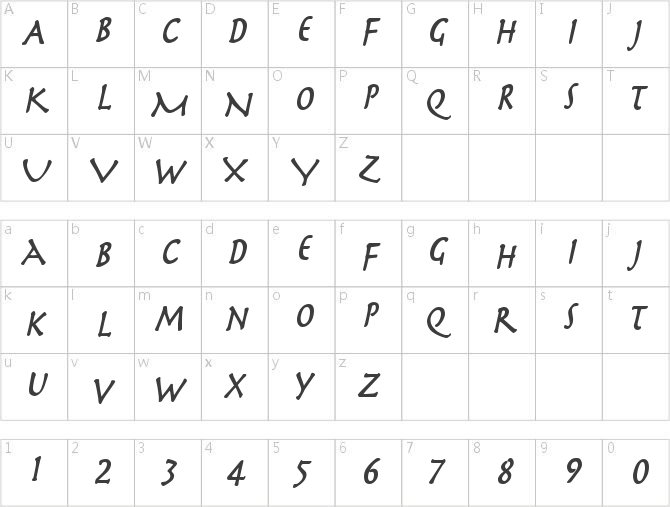
Mythology-Condensed-BoldItalic
Mythology-Condensed-BoldItalic介紹
Mythology-Condensed-BoldItalic字體字庫(kù)是一款讓人賞心悅目、百看不厭的英文字體,適合各類廣告和產(chǎn)品包裝設(shè)計(jì)應(yīng)用,字體大小0.07MB,格式為ttf字體,上傳用戶是Apple,作者/版權(quán)方為未知
Mythology-Condensed-BoldItalic效果圖